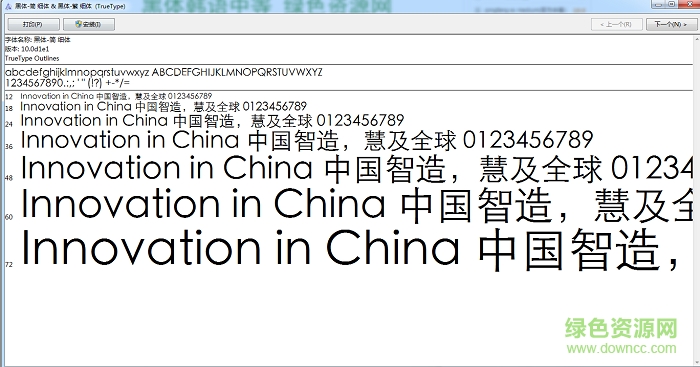
黑體 簡 細(xì)體字體是一款纖細(xì)的中文廣告字體,線條柔軟流暢,字形簡潔明快,結(jié)構(gòu)嚴(yán)謹(jǐn)勻稱,這款字體從外形上看雖然不夠精美卻十分實(shí)用,有需要者快來綠色資源網(wǎng)下載吧!
黑體字是現(xiàn)代漢字體系中最重要的字體之一。尤其是隨著20 世紀(jì)末電腦和互聯(lián)網(wǎng)的普及,黑體字的價值得到了進(jìn)一步體現(xiàn),它簡潔的筆畫特征與屏顯介質(zhì)特性相符,從而成為了當(dāng)今各種屏幕媒介中最有發(fā)展前景的字體。
粗黑、超粗黑(特黑)、大黑、細(xì)黑、美黑、宋黑、水黑、藝黑、氈筆黑、平黑等類型。